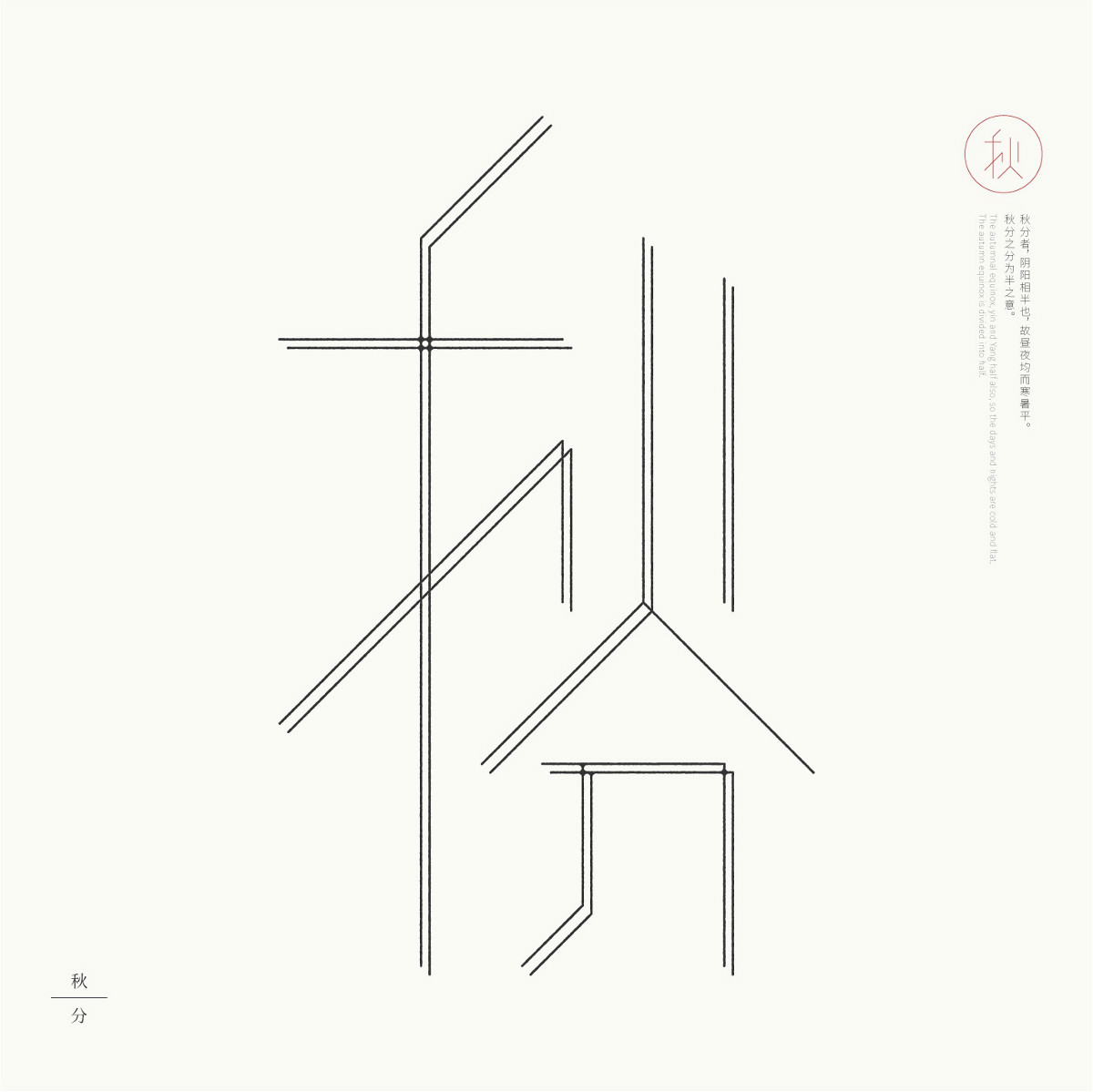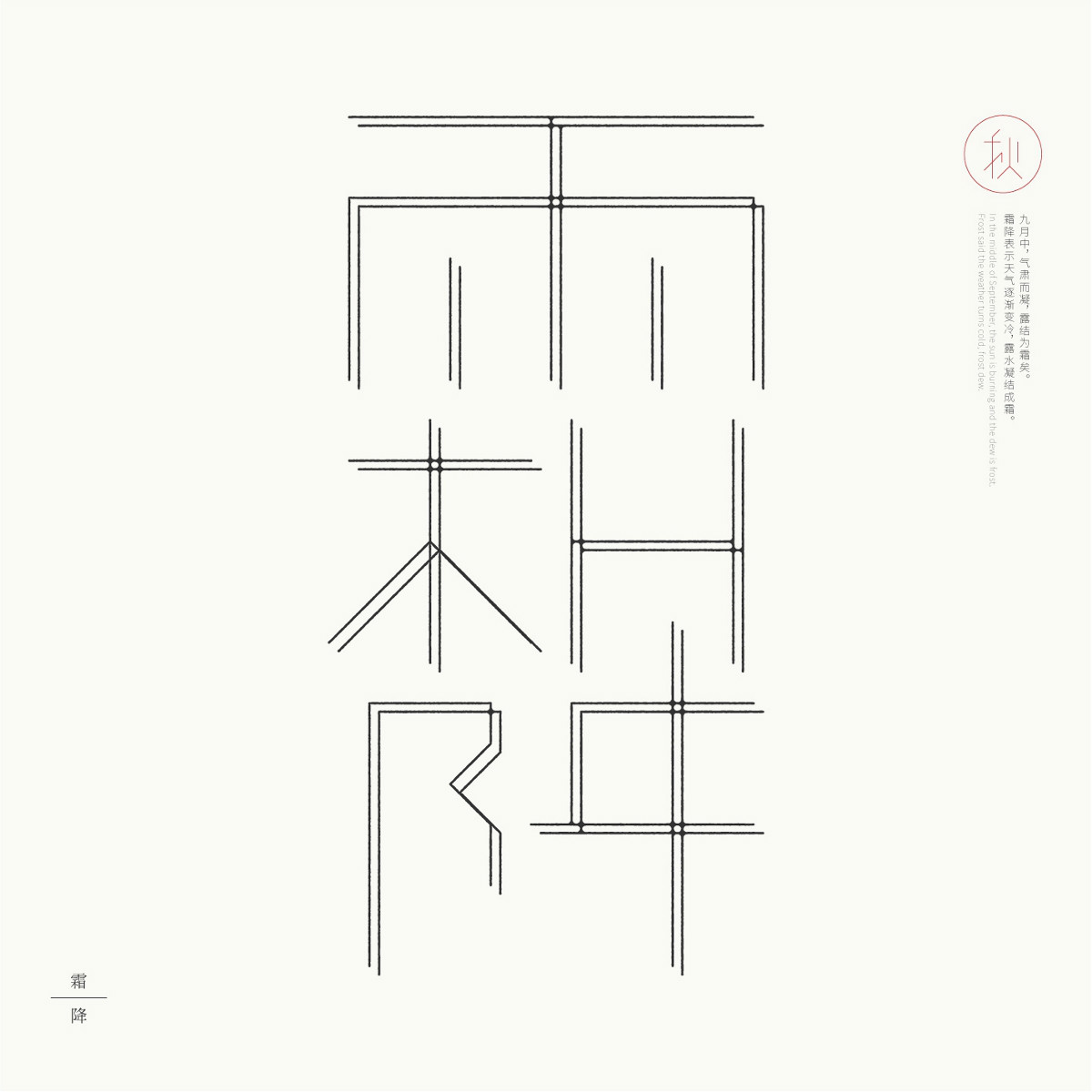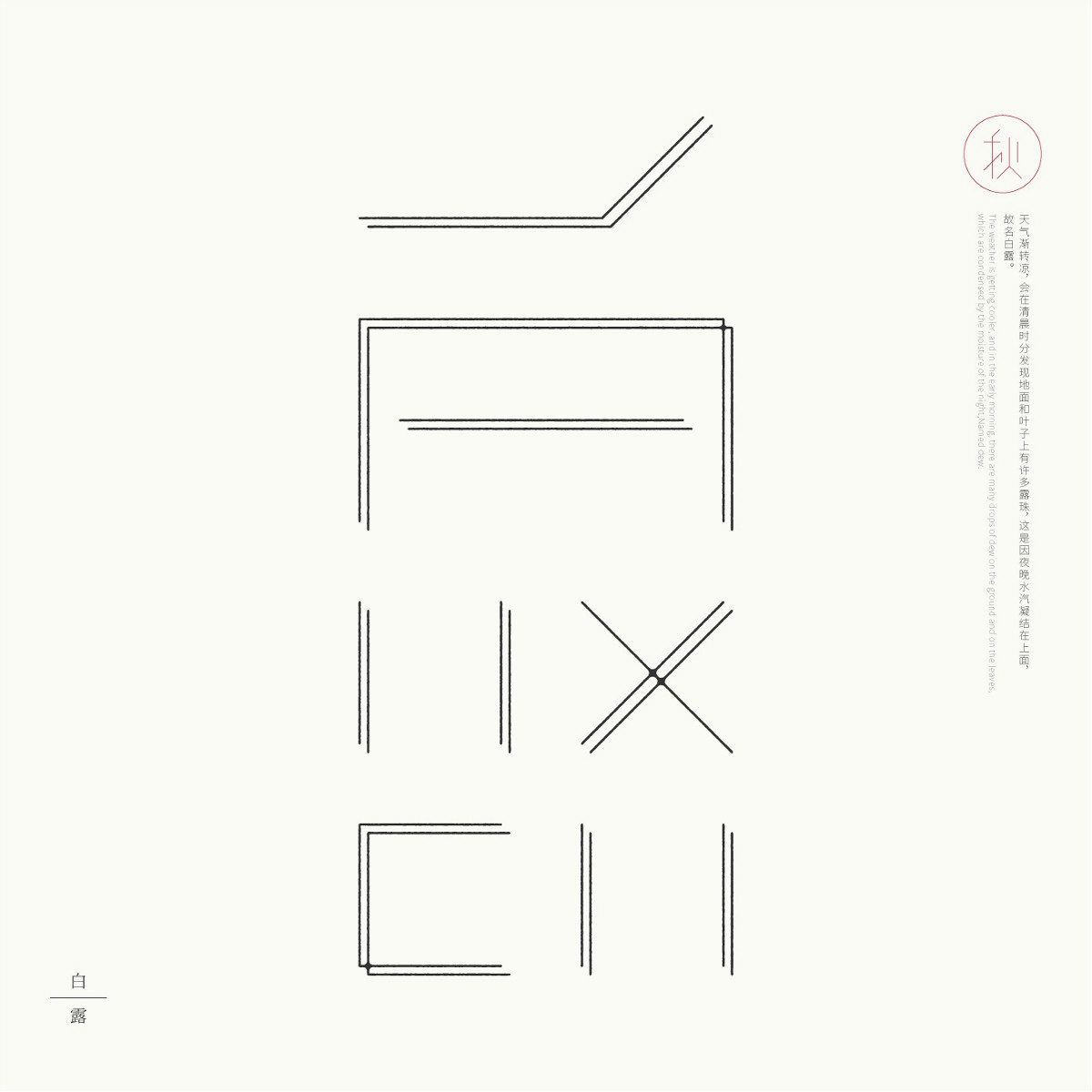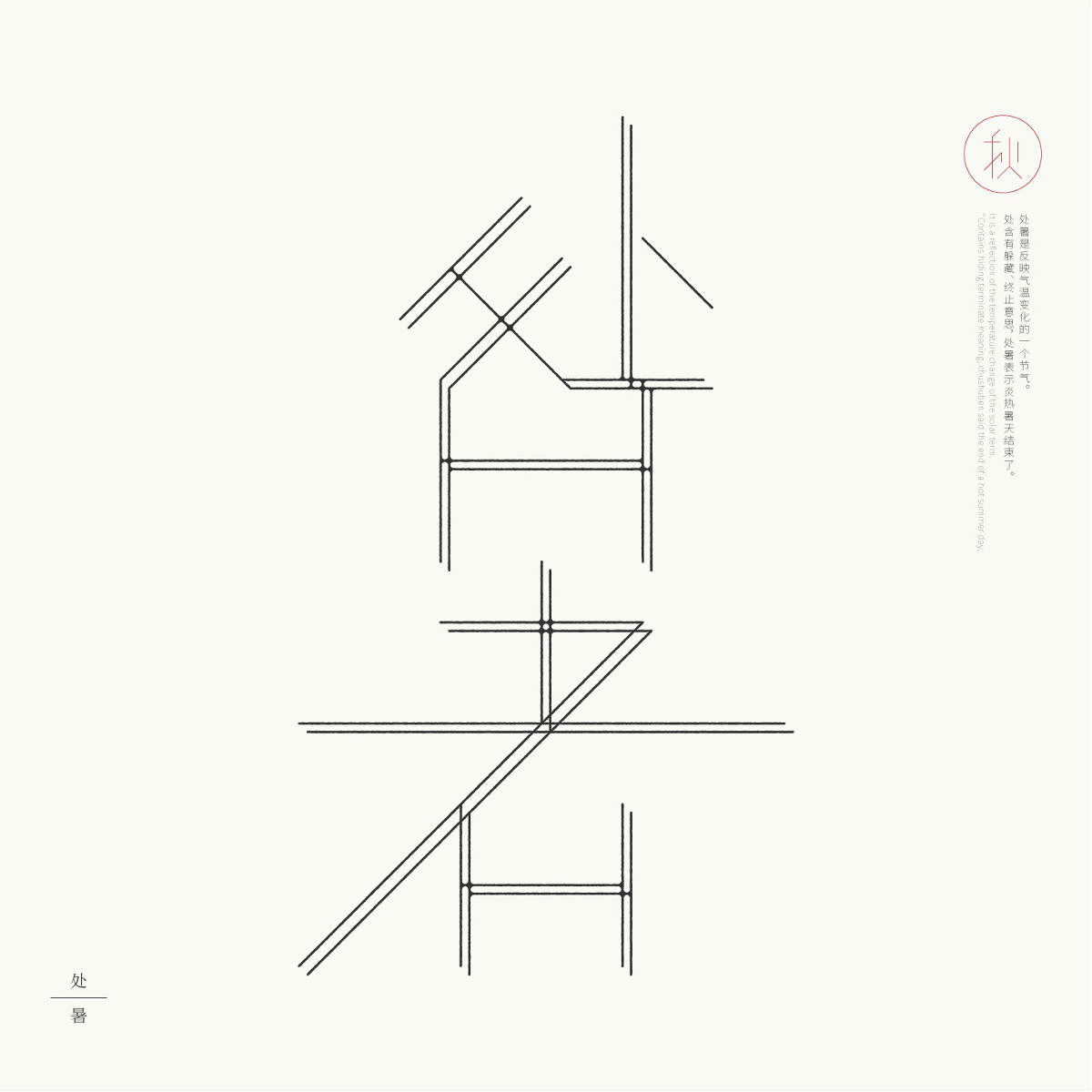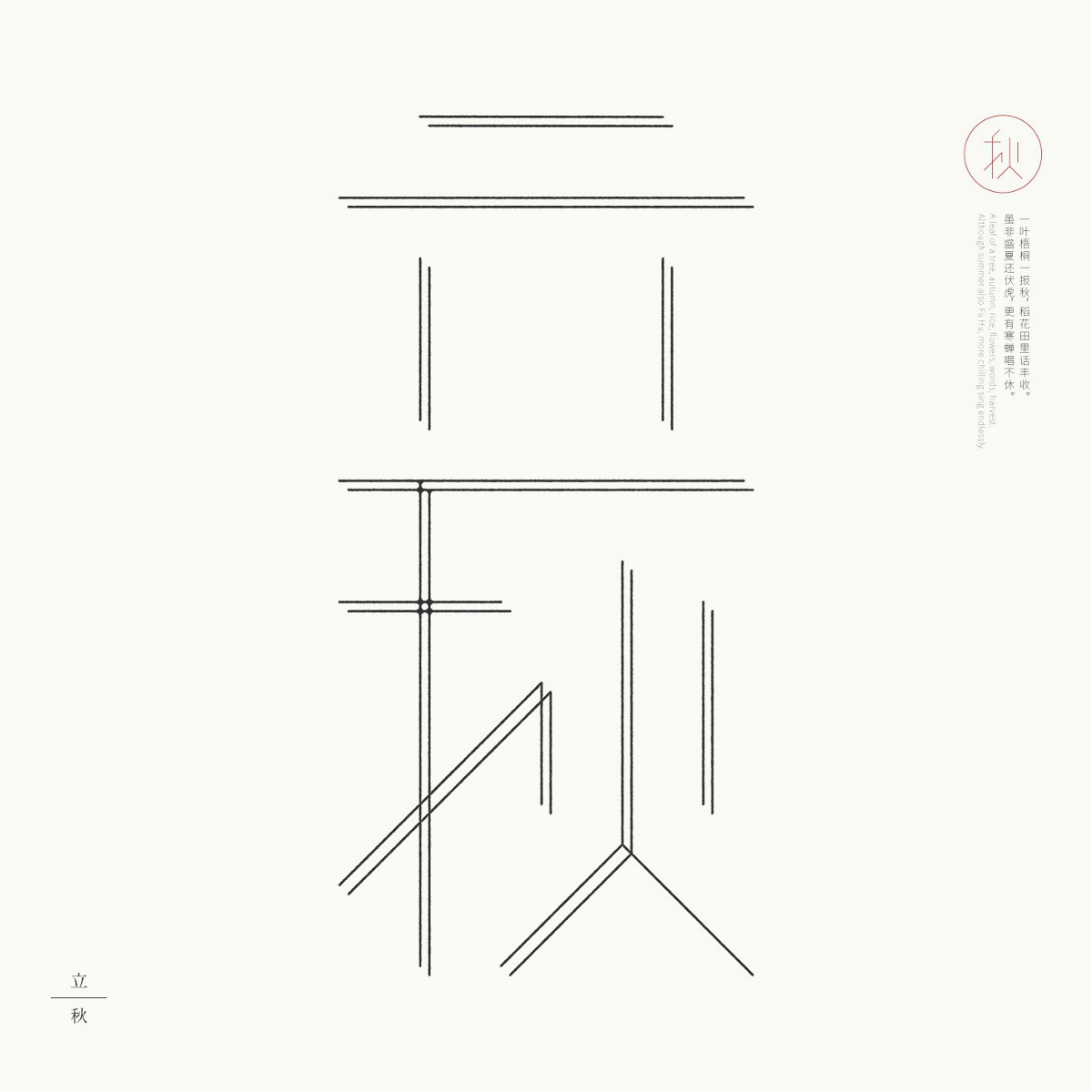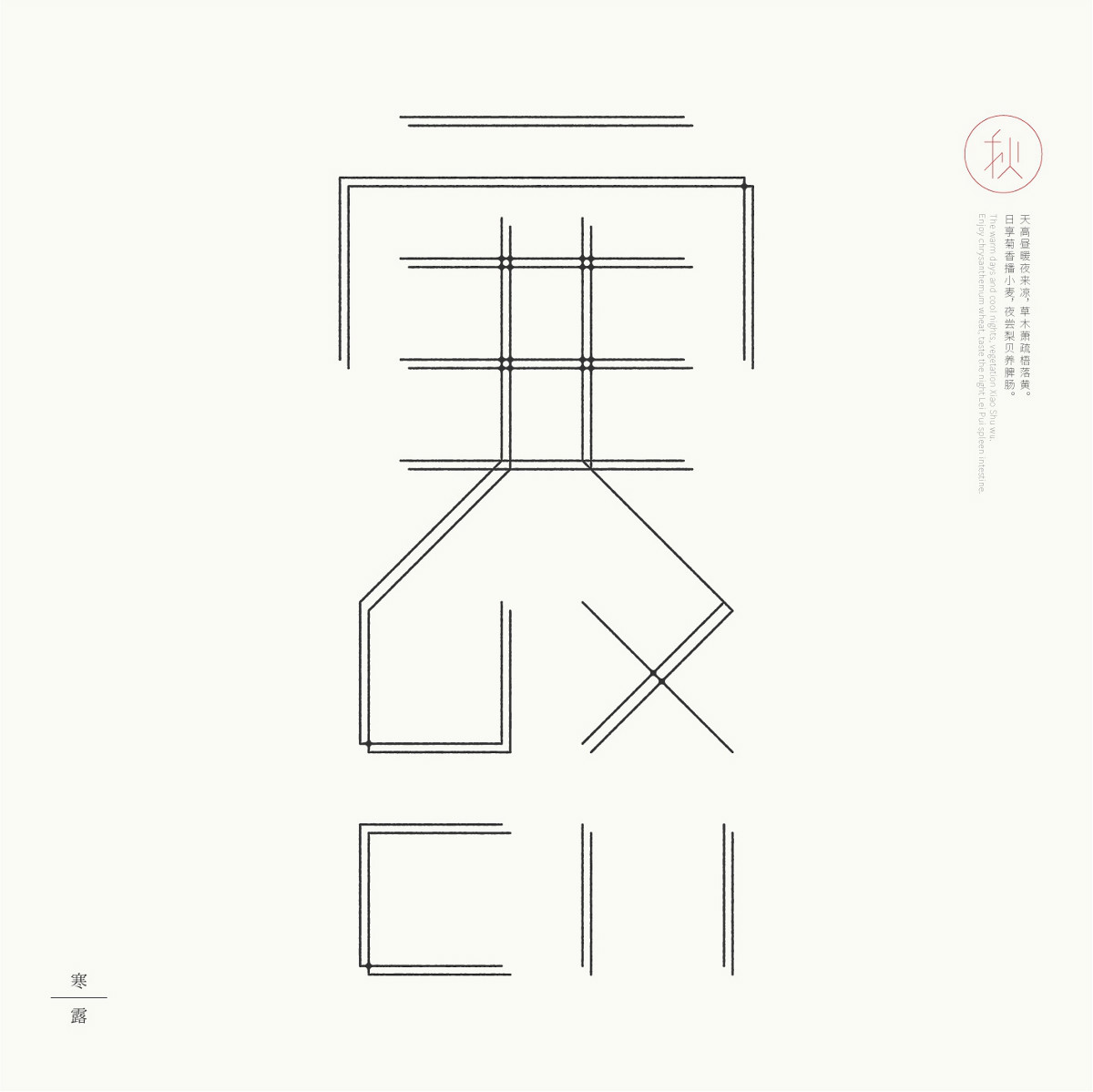
24節(jié)氣字體設(shè)計,簡約黑白藝術(shù)字體設(shè)計
24節(jié)氣字體設(shè)計,簡約黑白藝術(shù)字體設(shè)計24節(jié)氣字體設(shè)計,簡約黑白藝術(shù)字體設(shè)計
24節(jié)氣字體設(shè)計,簡約黑白藝術(shù)字體設(shè)計